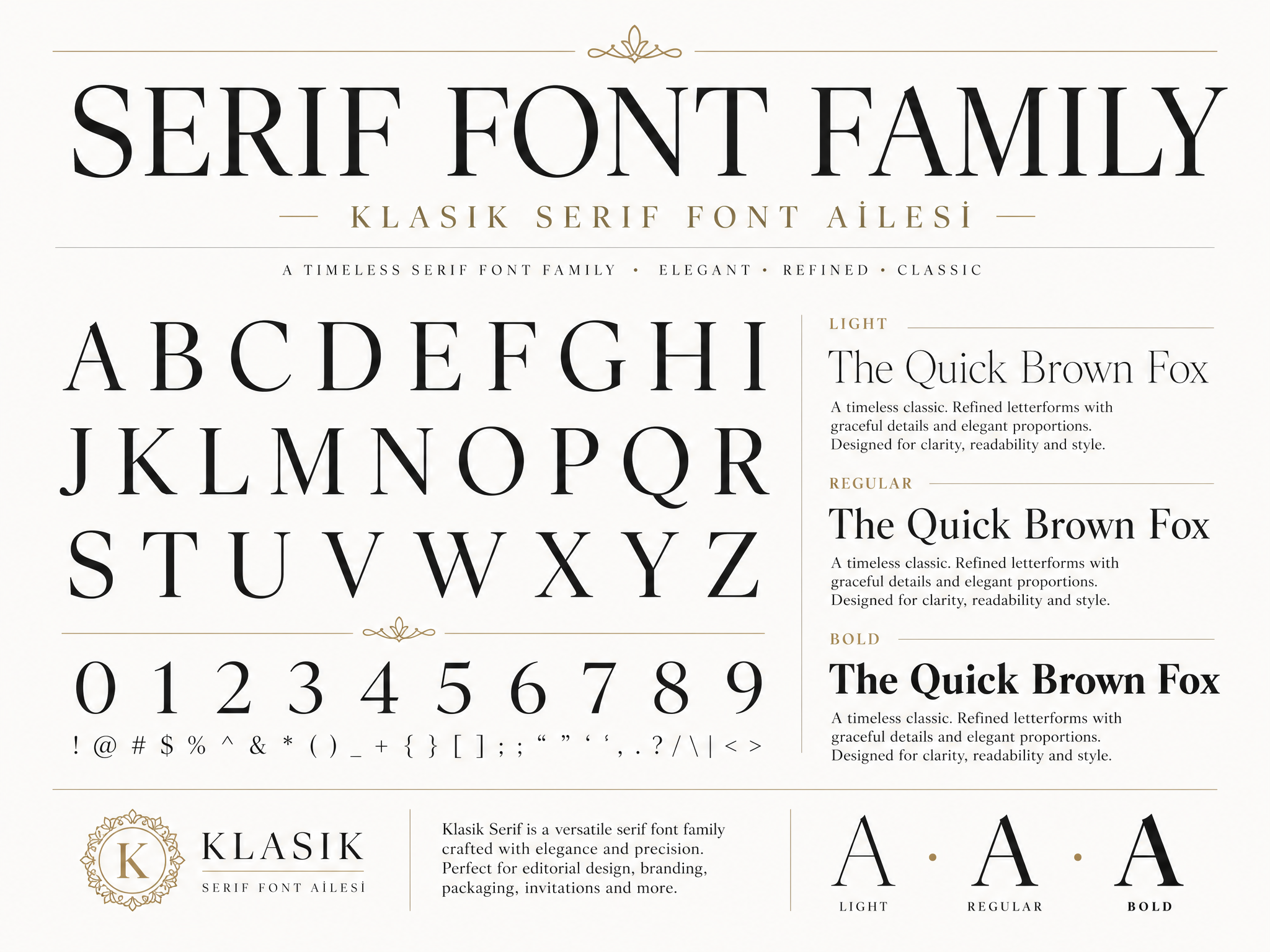
Klasik Serif Font Ailesi; editoryal tasarımlar, dergiler, kitap kapakları ve kurumsal kimlikler için zamansız bir zarafet sunan çok yönlü bir serif koleksiyonudur. Dengeli tırnak (serif) yapısı hem başlıklarda hem de uzun metinlerde yüksek okunabilirlik sağlar. Aile; Regular, Italic, Medium, Semibold ve Bold ağırlıklarını içerir; böylece güçlü bir tipografik hiyerarşi kurabilirsiniz. Tüm karakterler Türkçe karakter setini eksiksiz destekler. OTF, TTF ve web için WOFF formatlarında teslim edilir. Ticari ve kişisel projelerde kullanıma uygundur.
Klasik Serif Font Ailesi